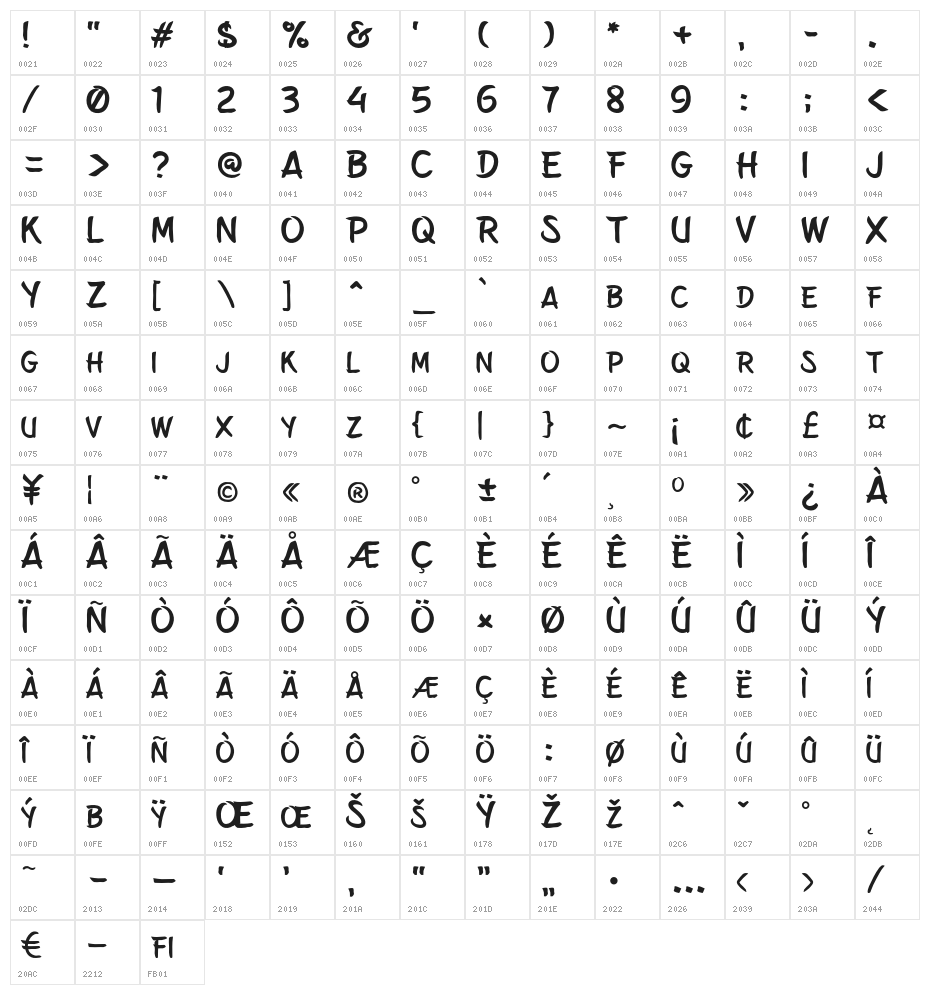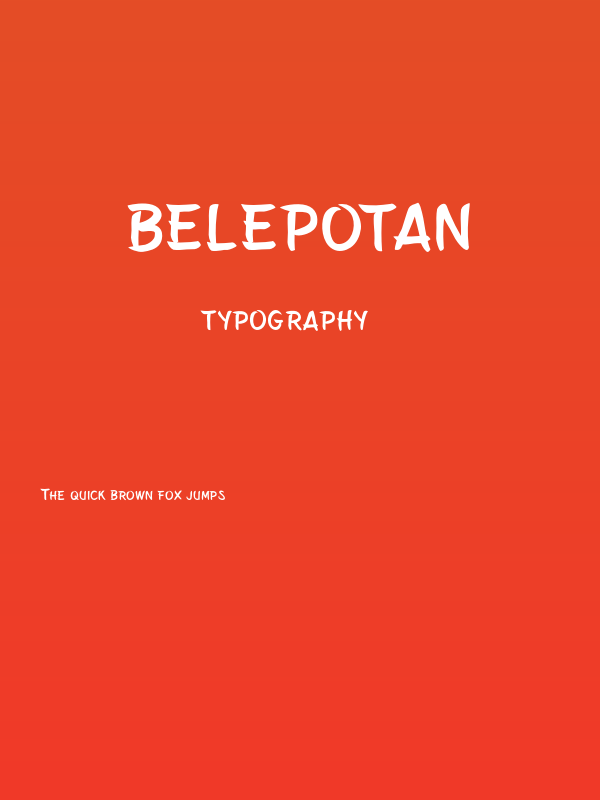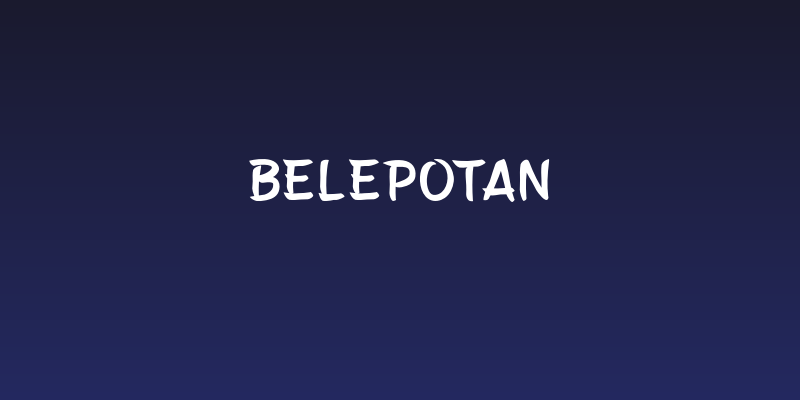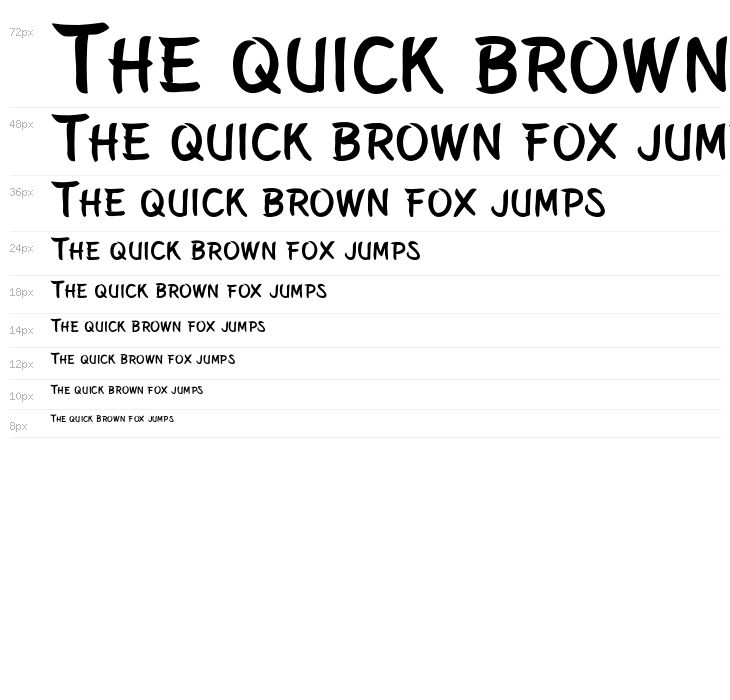
Belepotan Font
| श्रेणियाँ | Script |
| समग्र शैली | Decorative |
| उपयोग का मामला | Logos, Headlines, Posters |
| सुझाए गए प्रोजेक्ट | Ideal for children's books, playful branding, casual invitations, and creative posters. |
Belepotan